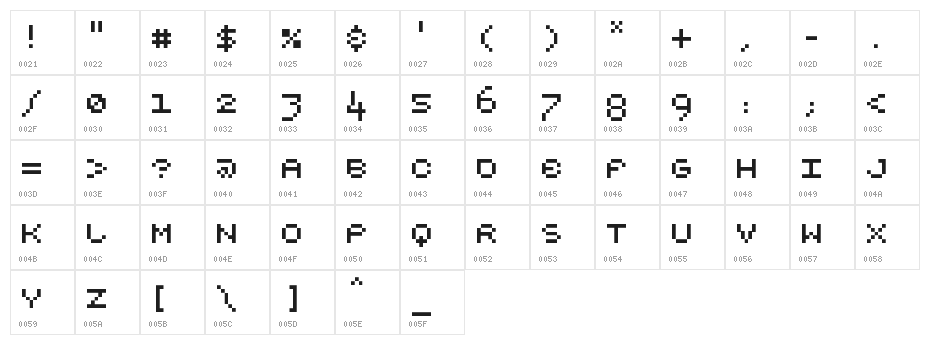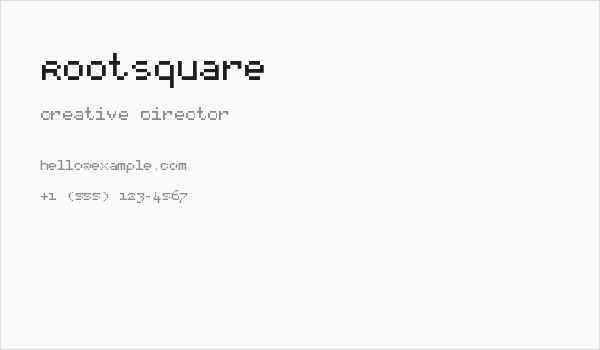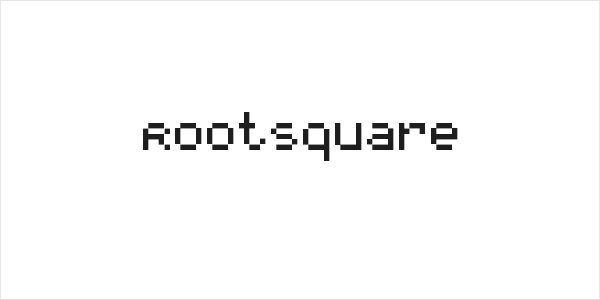
RootSquare Font
| Kategorien | Pixel |
| Gesamtstil | Retro |
| Anwendungsfall | Logos, Headlines, Digital Art |
| Vorgeschlagene Projekte | Ideal for retro video game graphics, tech-themed posters, digital art projects, and any design requiring a nostalgic digital feel. |